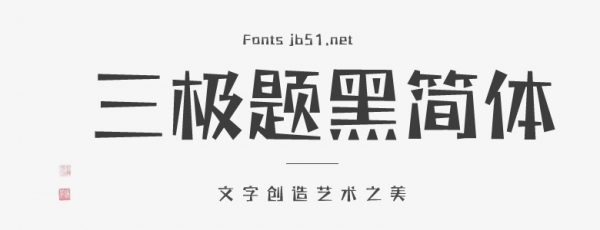
三極題黑體由梯形衍變出了這款字,梯形狀的點類似小方塊,橫豎粗細有變化,整體字的感覺帶有些活躍感又不失方正感。標題、標題肯定需要又有方正感有需要有特點化,三極題黑體既能滿足大標題小標題又適用于內文表達,是款全面覆蓋的字體,用于標題中塊狀化的字體醒目又有風格感,讓人記憶猶新,用于內文中規(guī)整又不失活躍感,讓人印象深刻。所以選擇三極題黑體,性價比極高,風格與特點化突出,適用于各種書寫印刷文本需求,是款必選的字體。